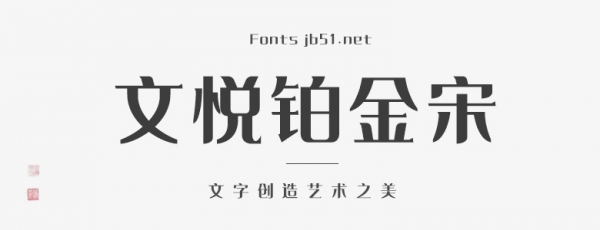
文悅鉑金宋是一款賞心悅目的藝術(shù)字體,字體線條粗細(xì)適中,筆畫隨性,結(jié)構(gòu)灑脫自在,具有很好的視覺(jué)感,適合于文化類的宣傳設(shè)計(jì)、商業(yè)類品牌的廣告和產(chǎn)品包裝設(shè)計(jì)以及個(gè)性化文字排版等較多場(chǎng)景。